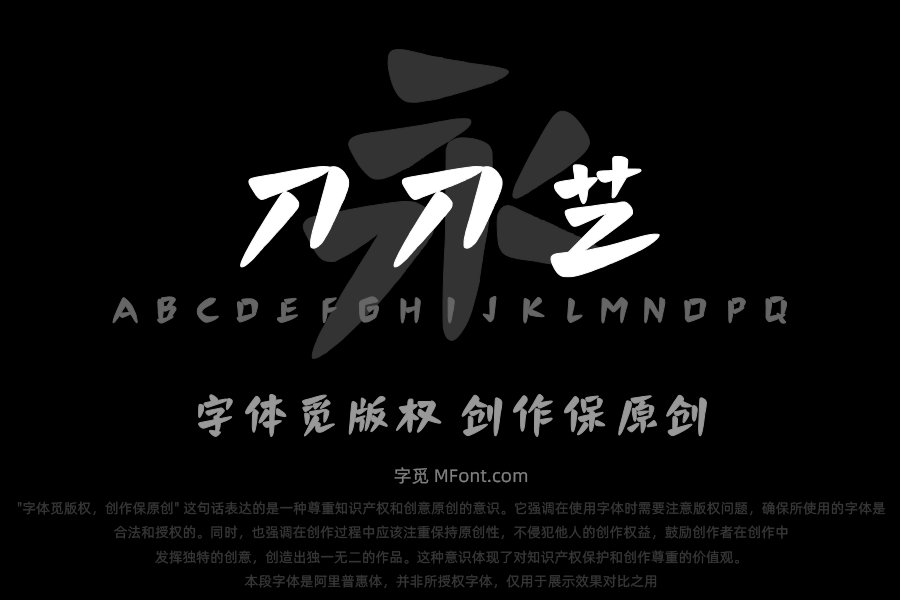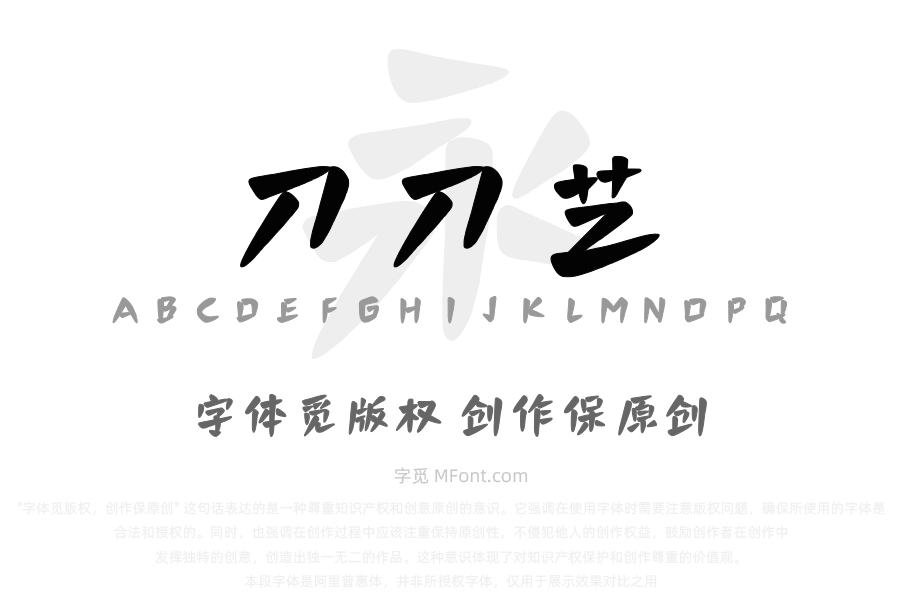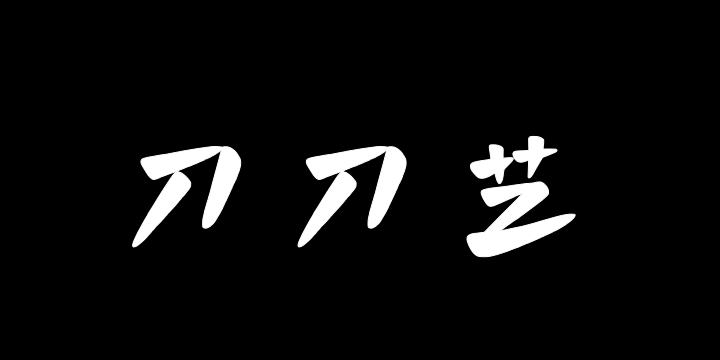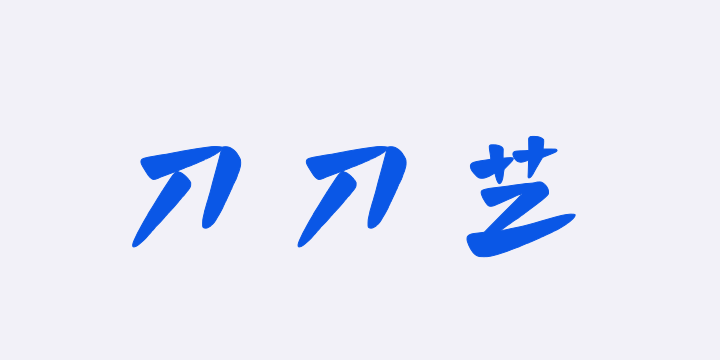
字潮刀刀艺
关于字潮刀刀艺字体字库信息
字体全名: 字潮刀刀艺
铸字厂: 字潮字库
设计师: 丁道华
字体简介: 字潮刀刀艺设计灵感汲取自中国传统篆刻艺术,将古老文字中的拙朴与厚重,巧妙融入现代设计的简约语言与鲜明个性之中。不仅保留了篆刻字体特有的笔墨流畅感与刀石刻痕的自然意趣,更赋予每个字以生动的力量与节奏。